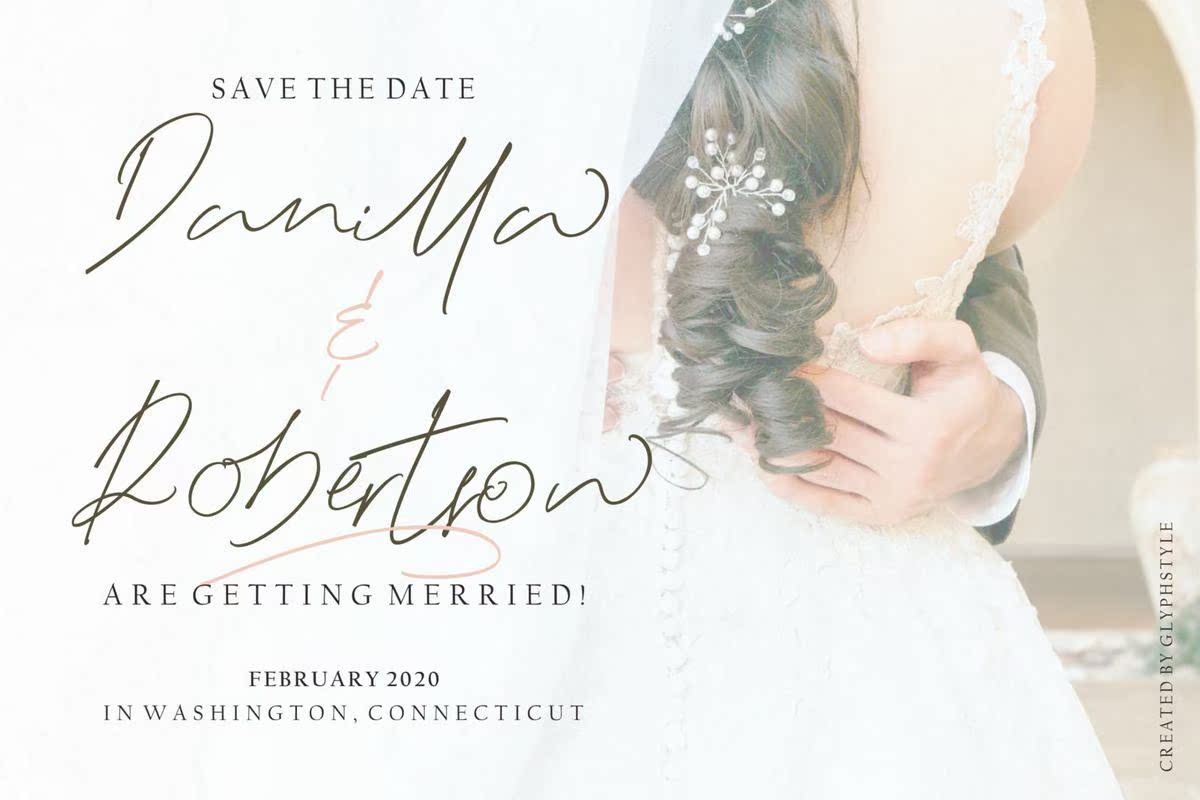
Black Angeles签名文本具有自然风格和流动性。具有自然和刮痕的美丽和传奇色彩。此签名适用于婚礼、水印、品牌推广,如采访、名片、产品徽标等。Black Angeles签名适用于品牌项目、徽标、婚礼设计、社交媒体、广告、产品包装、产品设计、标签、摄影、,水印、邀请函、文具和任何需要手写签名的项目。黑天使签名文本具有自然的风格和流动性。具有自然和划痕的美丽和美丽的字体。此签名适用于婚礼、水印、品牌,如采访、名片、产品标识等。黑天使适用于品牌项目、标识、婚礼设计,社交媒体、广告、产品包装、产品设计、标签、摄影、水印、邀请函、文具以及任何需要感知和书写签名的项目。